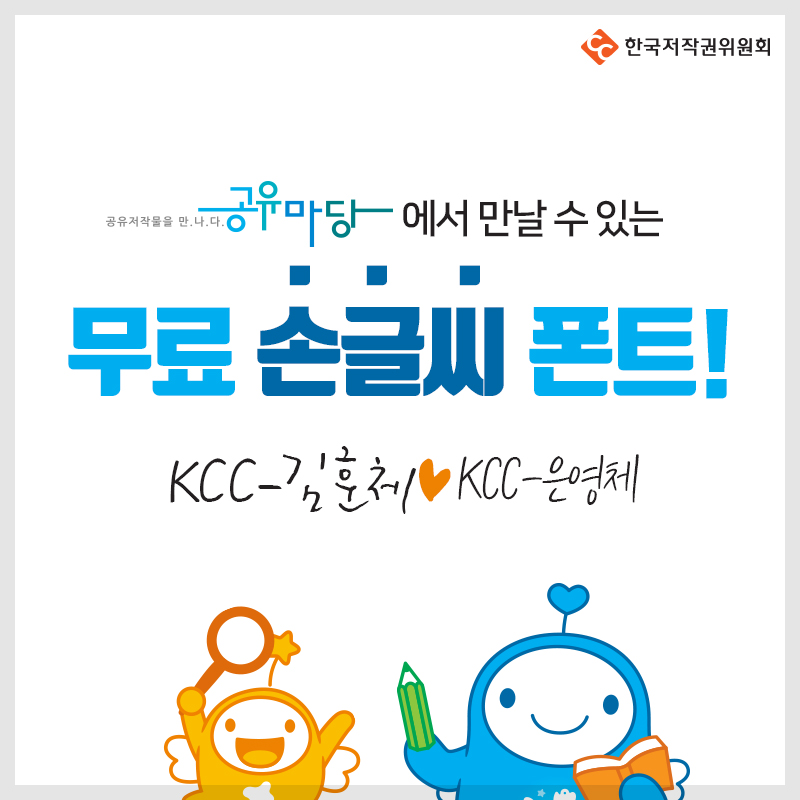
한국저작권위원회, 소설가 김훈체 포함 무료 폰트 2종 배포
한국저작권위원회가 일반 국민 누구나 저작권 걱정 없이 마음껏 창작활동 등을 할 수 있도록 ‘KCC-김훈체’와 ‘KCC-은영체’를 개발했다.
‘KCC-김훈체’는 소설 <남한산성>을 쓴 김훈 작가의 손글씨를 기증받아 폰트화한 서체로, 김훈 작가는 아직도 컴퓨터가 아닌 원고지에 집필하는 몇 안 남은 작가로 그 의미가 매우 특별하다. ‘KCC-김훈체’와 함께 공개된 ‘KCC-은영체’는 한국저작권위원회가 2016년 진행한 국민저작물 보물찾기 공모전을 통해 선정한 황은영씨의 손글씨를 폰트화한 서체로 대표 국민 손글씨 폰트라고 할 수 있다.
한편 저작권위원회는 앞으로도 유명한 작가들의 손글씨 등 다양한 폰트를 개발하여 국민들에게 제공할 계획이라고 밝혔다.